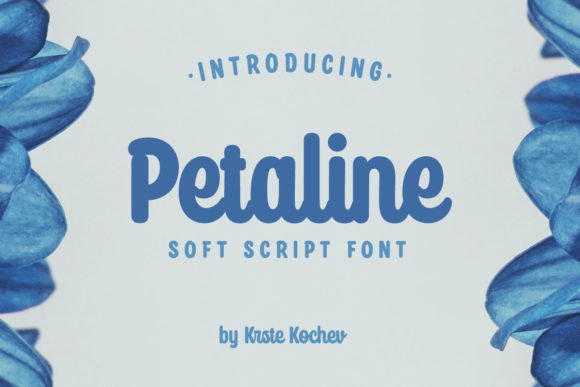
Petaline - Soft Script
Découvrez Petaline : Une Police Soft Script Élégant et Versatile
Petaline est une police soft script raffinée qui allie douceur et modernité. Avec ses courbes organiques et son caractère bienveillant, elle apporte une touche naturelle et chaleureuse à vos projets. Que vous travailliez sur un site web, une carte d’affaires ou un design graphique, Petaline apporte une élégance subtile qui se démarque par sa simplicité et sa personnalisation. De plus, sa compatibilité avec les logiciels open-type en fait un choix idéal pour les professionnels exigeants.
- Personnalisation infinie : Des variantes de poids, de taille et de style pour s’adapter à vos besoins.
- Charme naturel : Ses traits fluides et ses finissements organiques créent une ambiance authentique etaconfortante.
Ce qui rend Petaline vraiment spécial, c’est sa capacité à s’adapter à tous les styles. Que vous souhaitiez un look romantique, professionnel ou créatif, cette police soft script offre une base solide et un potentiel infini de modification. Grâce à ses options de personnalisation, vous pouvez facilement intégrer cette police à vos projets sans compromettre la lisibilité ou l’esthétique.
Pourquoi Choisir Petaline ?
En plus de ses atouts esthétiques, Petaline est conçue pour être pratique. Son format open-type assure une compatibilité maximale avec les logiciels de traitement de texte et de conception graphique. Cela signifie que vous pouvez l’utiliser sans souci, que vous soyez un designer débutant ou un professionnel expérimenté. De plus, sa polyvalence en fait un choix populaire pour les marques cherchant à évoquer une image douce, moderne et raffinée.
En résumé, Petaline est bien plus qu’une simple police : c’est un outil créatif qui transforme vos projets en œuvres d’art. Grâce à sa combinaison unique de beauté et de fonctionnalité, elle est un must-have pour quiconque souhaite ajouter une touche d’élégance à ses travaux.